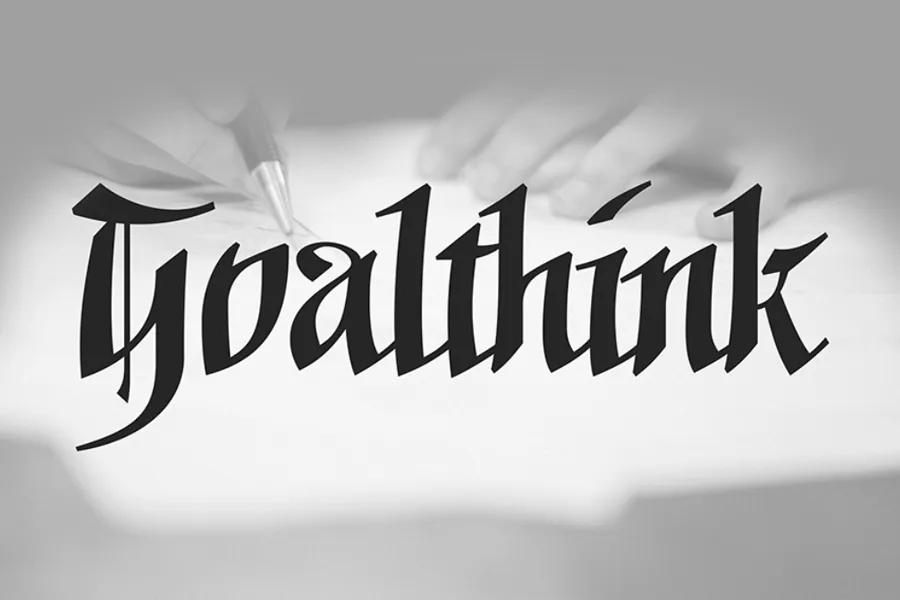
Goalthink Typeface – Download Grátis
Esta fonte é especialmente projetada para aqueles que buscam adicionar suavidade a seus trabalhos. Introduzimos Goalthink Font! Desenvolvida e compartilhada por Tzu-yuan Yin, essa série de fontes se destina a ser uma reflexão da junção de fonts tradicionais de gothico e escrita à mão personalizada. Ideal para uso em design de logotipos, projetos artesanais, marcas, cerimônias casamento e muito mais. Tzu-yuan Yin introduziu Goalthink como uma variação do gothico, fazendo deste conjunto de fontes uma escolha perfeita para adicionar um toque suave a qualquer projeto. Nossa esperança é que você se divirta experimentando Inky Hand Script.